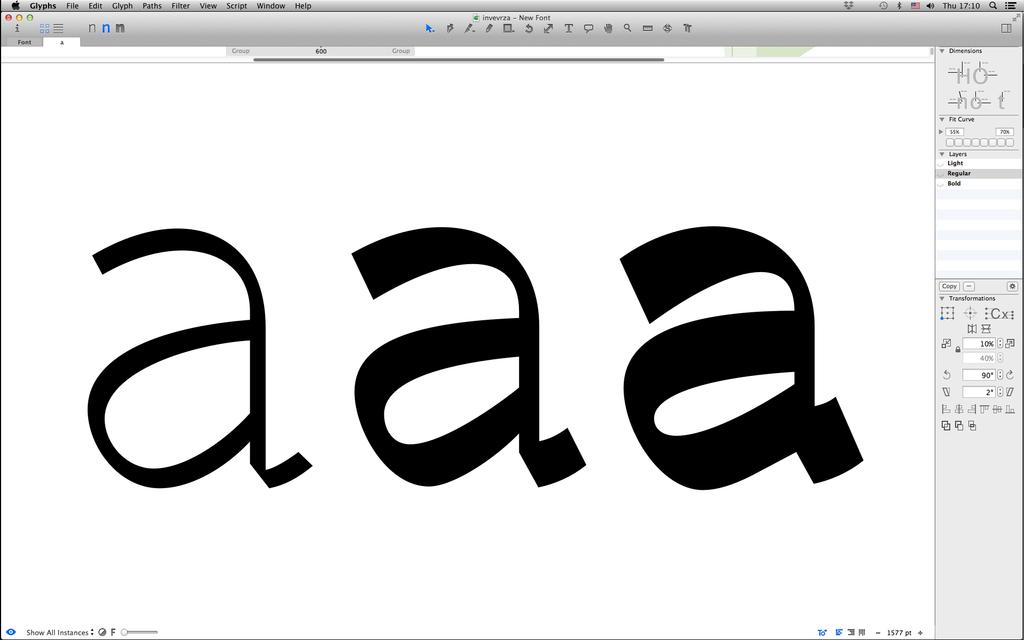
1 N G I S E D A M S Í P
2 *UDðFNÀ SRGRED IRQWX Názvosloví GŒķN\ 6WHPV SŒķËN\ &URVVEDUV šikmé tahy / Daigonal Strokes EŒķŕND %RZOV serify / Srifs Workshop Seznam Font Jockey MDN SRUR]XPÔW W\SRJUDðFNÒPX SķVPX D Y\EUDW WR SUDYÒ
3 *UDðFNÀ SRGRED IRQWX Názvosloví Workshop Seznam Font Jockey MDN SRUR]XPÔW W\SRJUDðFNÒPX SķVPX D Y\EUDW WR SUDYÒ VHULI\ V REOťPL QÀEÔK\ bracketed serif VHULI\ EH] QÀEÔKX straight serif deskovitý serif slab serif skrytý serif bez serifu sans serif
4 *UDðFNÀ SRGRED IRQWX Názvosloví Font Jockey Workshop Seznam Font Jockey MDN SRUR]XPÔW W\SRJUDðFNÒPX SķVPX D Y\EUDW WR SUDYÒ oboustranný srif Bilateral Serif GŒķN Stem spodní dotah Descender hrot Apex SŒķËND Crossbar klínovitý serif Triangular serif HpQegd HpQegd AnbRarS SŒķËND Crossbar QÀEÔK VHULIX Bracket Oblý tah Rounded Stroke ]ÀŒH] Vertex EŒķŕNR Bowl oko Eye chvost Tail oblouk Ark šikmý tah Diagonal Stroke chvost Tail trn Spur chvost Tail spojka Link ucho Ear zrno Ball terminal KRUQķ GRDũQLFH Ascender VP\ËND Loop klínovitý serif Beak KŒEHW Spine
5 *UDðFNÀ SRGRED IRQWX Názvosloví Workshop Seznam Font Jockey MDN SRUR]XPÔW W\SRJUDðFNÒPX SķVPX D Y\EUDW WR SUDYÒ Řqky Çňl VWXSHń písma Font Size DNFHQWRYÀ GRWDũQķFH KRUQķ GRWDũQLFH $VFHQGHU /LQH YHU]ÀONRYÀ GRWDũQLFH &DS /LQH PķQXVNRYÀ GRWDũQLFH 0HDQ /LQH =ÀNODGQķ GRWDũQLFH WDNÒ ŜËDŒķ %DVH /LQH 'ROQķ GRWDũQLFH 'HVFHQGHU /LQH Horní dotah Ascender hodnota prokladu psma Leading VWŒHGQķ výška SķVPD ; KHLJKW Spodní dotah Descender výška verzálek Cap Height
6 s á n e j o r t
7 / typy nástrojů 1 ploché pero broad nib 2 ostré pero pointed nib
8 / 1 / ploché pero / plochý štětec stupňů pouze translace tah tah
9 / 1 / ploché pero / šablona
10 / 2 / ostré pero / ostrá štětec cca. 50 stupňů práce s přítlakem tah+tlak tah tah
11 / 2 / ostré pero / šablona 50 stupňů
12 / 3 / kulaté pero nezávislé na úhlu tvoří kostru písma / rukopisu
14 a a aa / klasifikace / historie a a aa
15 a / kombinace historie a nástroje + = commercialtype marian
16 / kombinace nástroje a techniky +a = urtd - odesta
17 / kombinace dvou klasifikací a+a = dizajndesign - kontrast grotesk
18 / kombinace osoby a modulární kostry + = suitcase - ladislav
19
20 / idea kombinací dvou a více dříve nesouvisejících věcí použitím nástroje v novém kontextu nečekaným / nepovoleným použitím nástroje aplikací pravidla na sadu znaků přivedením pravidla do extrému potlačením existujích pravidel typecooker
21 a p m a r y r t e
22 / typecooker
23 / tloušťka duktus kolik duktů mohu vyrobit? kolik jich opravdu potřebuji? pracuji jak s černou, tak s negativním prostorem aaaaaaa Thin, ExtraLight, Light, Regular, Medium, Bold, ExtraBold
24 / šířka vvv kolik šířek mohu vyrobit? je kondenzovaná nebo široká proporce vůbec vhodná pro toto písmo? aaaaa Compressed, Condensed, Regular, Wide, Extended
25 / typ kontrastu jaký kontrast použiji? jaký nástroj byl použit na tvorbů liter? noa noa pointed nib / broad nib
26 / množství kontrastu kolik kontrastu je možné použít? kolik kontrastu je vhodné? aaaaa??? nízký kontrast, vysoký kontrast
27 HELA, 7 ŘEZŮ tučné tahy skákaly po znacích jako blechy po hřišti. Tenká diakritika zašila švy literám aby textura byla zachována. čísla 2, 4 a 7 nezůstala pozadu a trojčila do rytmu duktů. Jen tečky zase stály na konci.
28 / patky serify tvořím patkové nebo bezpatkové písmo? jaké patky použiji? rovné, s náběhem, symetrické, asymetrické hh aa bb patkové písmo, bezpatkové písmo
29 / použití text / display tvořím textové písmo nebo akcidenční? jaké bude použití tohoto písma? tisk, noviny, časopisy, web, čtečky, plakáty, umění? a a aa aa textové, akcidenční, display
30 o r p s e c
31 y ě r ě m s í m o p u p v n é e ů i n n g v í y t á s r h a p a v o s r o l ř e p t a ě m v m s e s l í y e p t p i u u n t i o s č k d r ž o a m o l d ý a s z n í í ž c ž í a e j v l u á á z d z ů o ž u p h o y z m s t j o ě r ě n b a r a o n u v, k t u a e l r v o z r k a ú d z oldřich menhart, 1957 e n tvorba typografického písma a
32 / skica papír, tužka, pero nejlepší kamarádi designéra 1 / skicováním + vyplňováním
33 / skica 2 / vyšrafováním
34 / skica 3 / dvojitá tužka double pencil
35 / korektury
36 / digitalizace TIFF PPI+
37 / digitalizace pro každou literu nový dokument v PS 1000 x 1200 px horní dotažnice verzálky mínusky účaří spodní dotažnice
38 / software Glyphs - Mac - v této době nejlepší SW na písmo Fontlab - Win, Mac - v 5.2 je stará, v 6 je drahá Font Forge, Glyphr Studio (online) FontStruct, Font Creator
39
40
41
42 á z a l k a l d a i m í n d p v u a n r s ig e d s í p
43 / tloušťka tahu x <x / šířka oblého tahu by měla být vždy větší než šířka rovného tahu (platí pro oba směry)
44 / tloušťka tahu XX OK
45 / horizontální / vertikální tahy x <x / šířka svislého tahu by měla být vždy větší než šířka vodorovného tahu